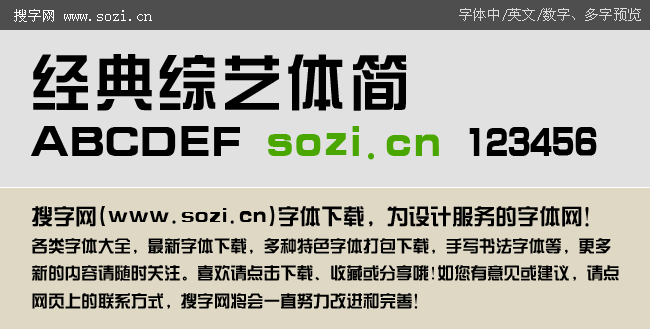
經(jīng)典綜藝體簡(jiǎn)
搜字網(wǎng)提供一款經(jīng)典綜藝體簡(jiǎn)下載。綜藝體是黑體的一種變體,也是藝術(shù)字的一種。特點(diǎn)是筆劃更粗,盡量將空間充滿(mǎn)。同時(shí)為了美觀(guān),對(duì)拐彎處的處理較為圓潤(rùn)。適用于廣告、報(bào)刊等的標(biāo)題及海報(bào)展板等設(shè)計(jì)場(chǎng)合使用。